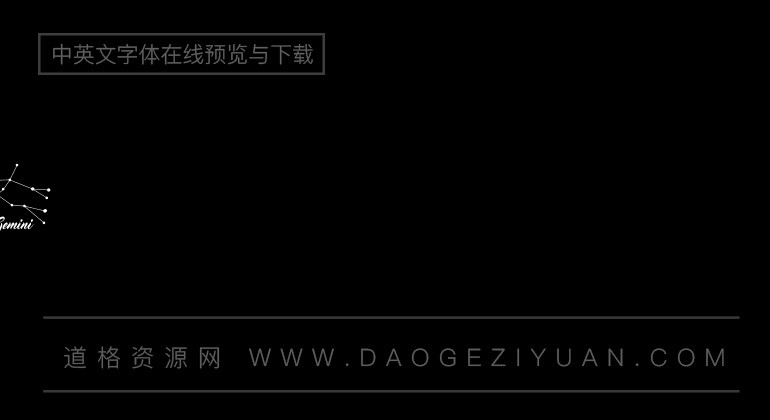
Constellations Ostia
Constellations Ostia 是一款精致的西文字体,由著名的设计师 Joana Correia 所设计。它的特点是拥有精致的细节,具有浓郁的情感,而且它的字体线条十分细腻,每一个字符都充满着浪漫的气息。它的字体可以用于商业、网页设计、平面设计等等,可以让你的作品更加出众。
Constellations Ostia是一款非常不错的手写艺术字体,具有很好的视觉感,适合于文化类的宣传设计、商业类品牌的广告和产品包装设计以及个性化文字排版等较多场景。
Constellations Ostia字符映射图